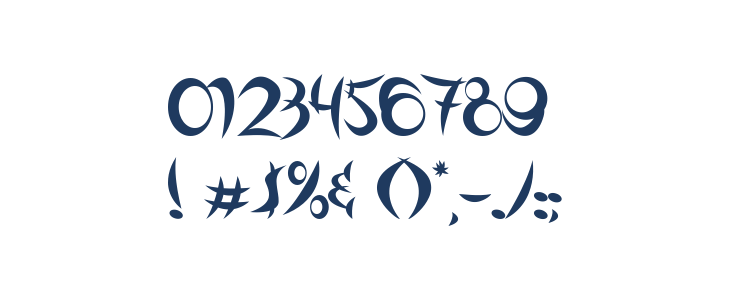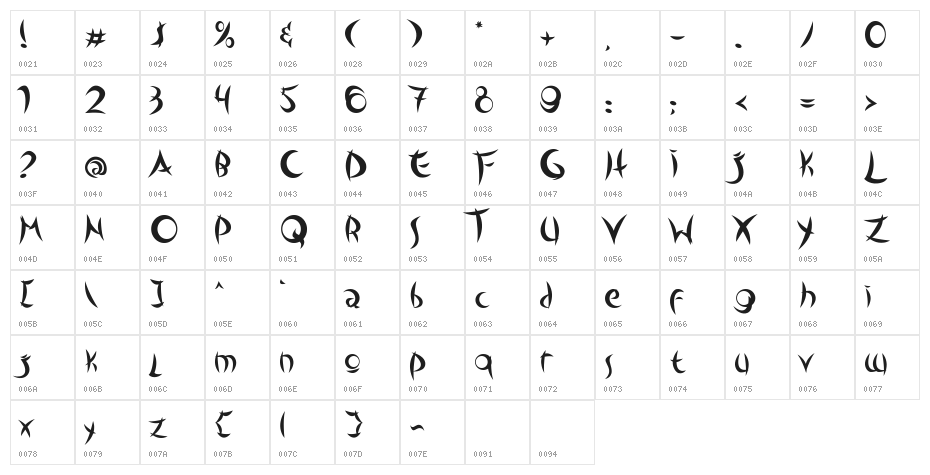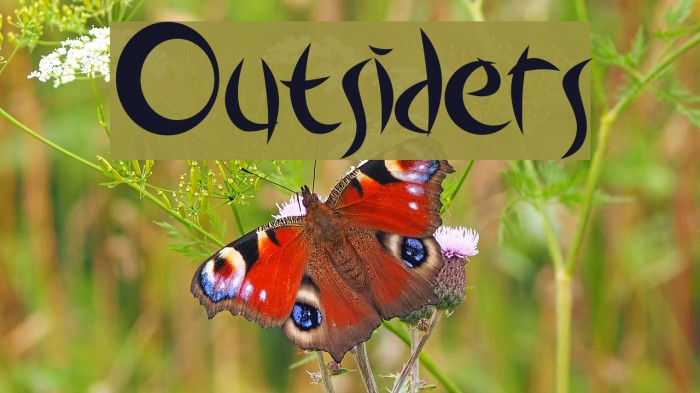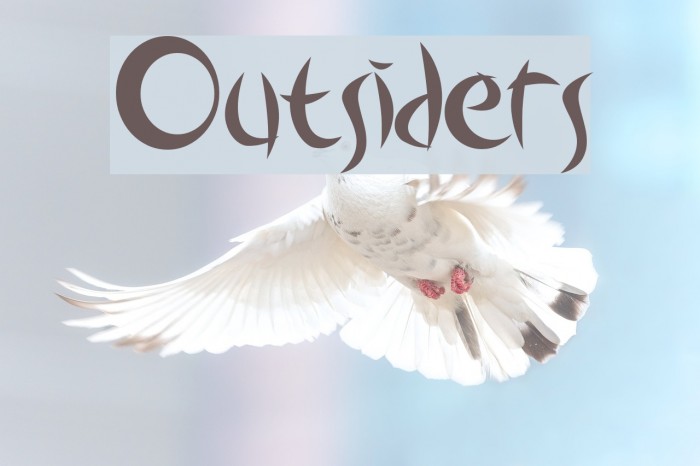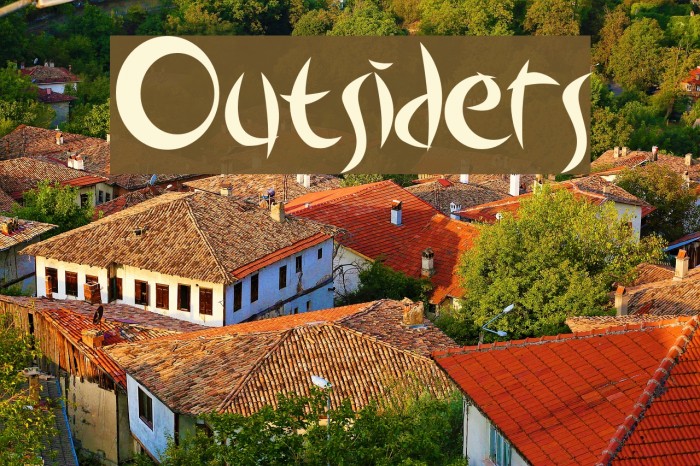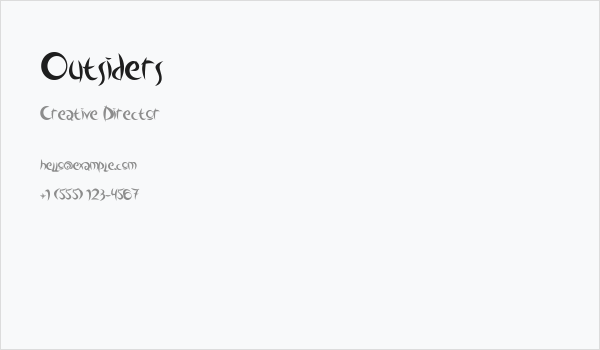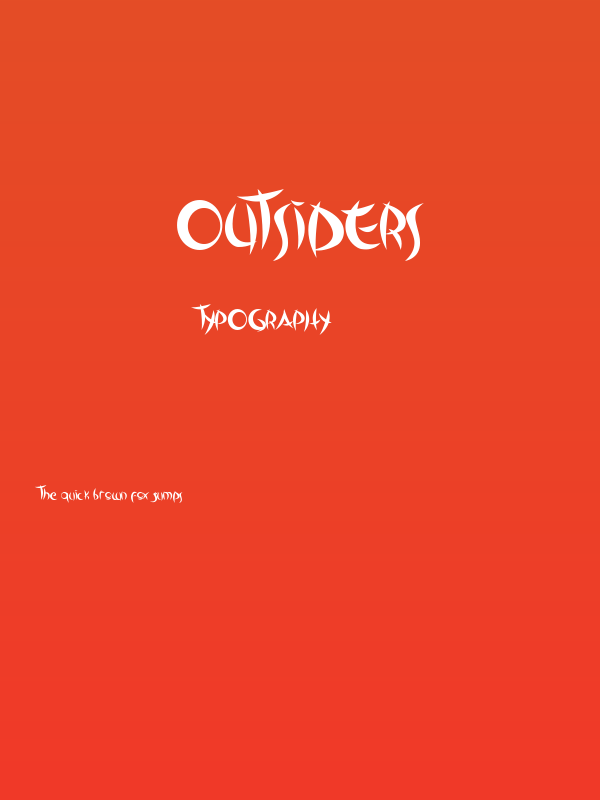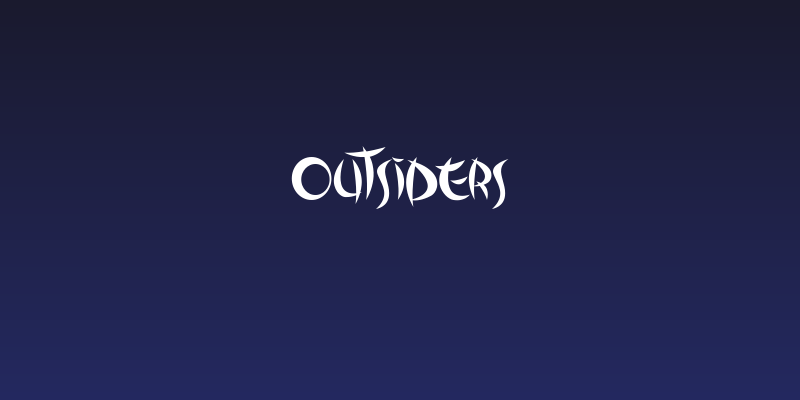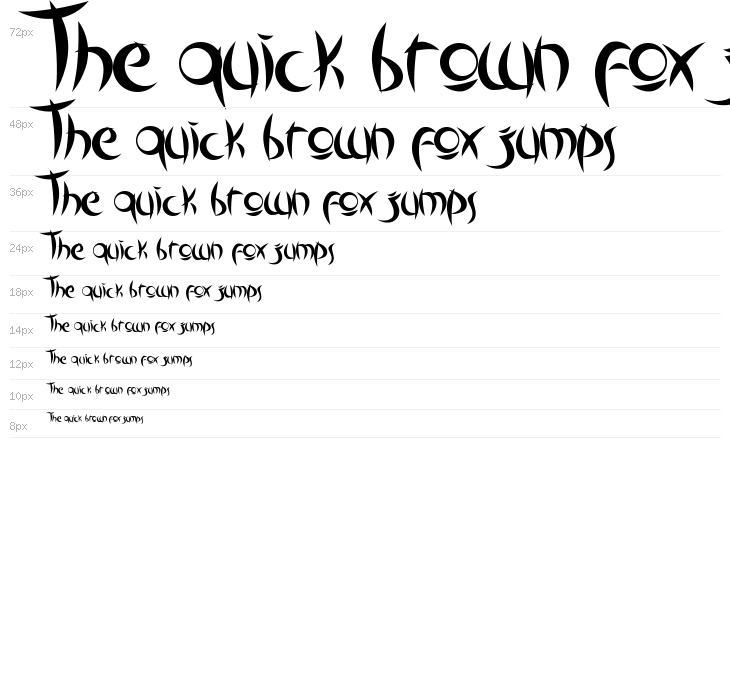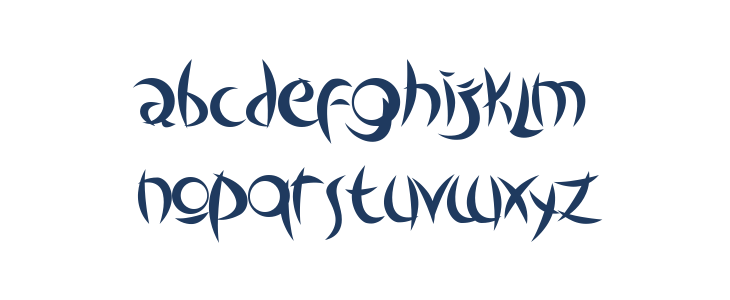
Outsiders Font
✎ Thick
| Kategorien | Thick |
| Anwendungsfall | Logos, Posters, Headlines |
| Vorgeschlagene Projekte | Ideal for music album covers, skateboarding brands, graffiti art, or any project seeking a rebellious and edgy look. |